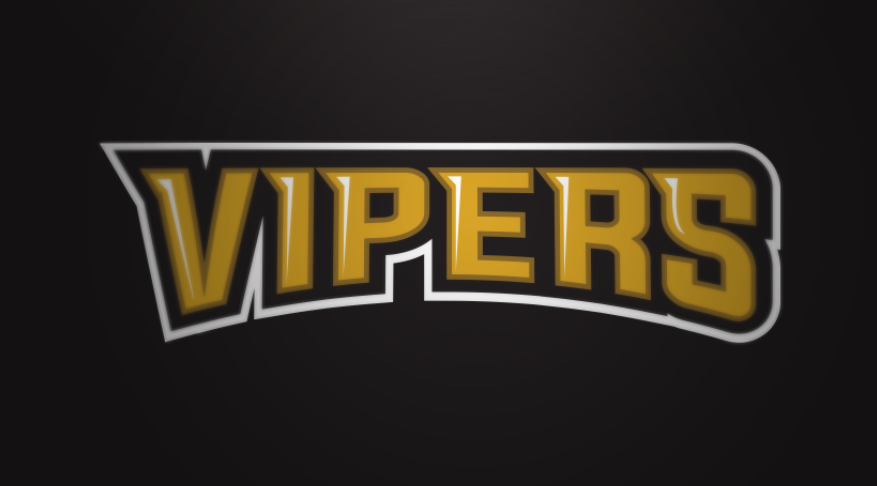
Ähnliche Schrift mit Dachansatz?
Ich suche diese Schrift oder auch eine ähnliche, muss nicht exakt dieselbe sein. Wichtig ist mir nur die ungefähre Dicke des Stamms und die kleinen Dachansätze oben links der Buchstaben. Dankbar für Hilfe!